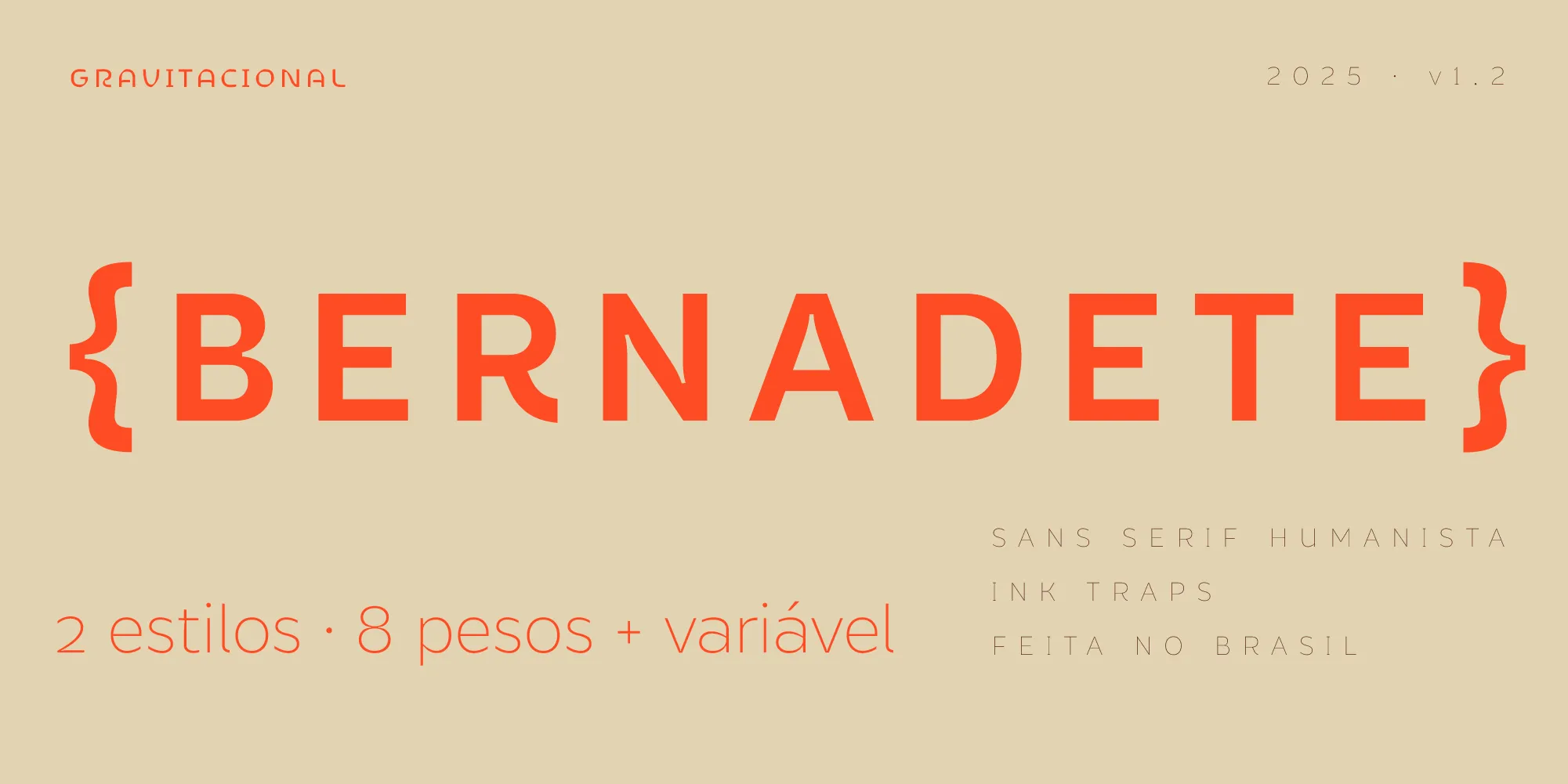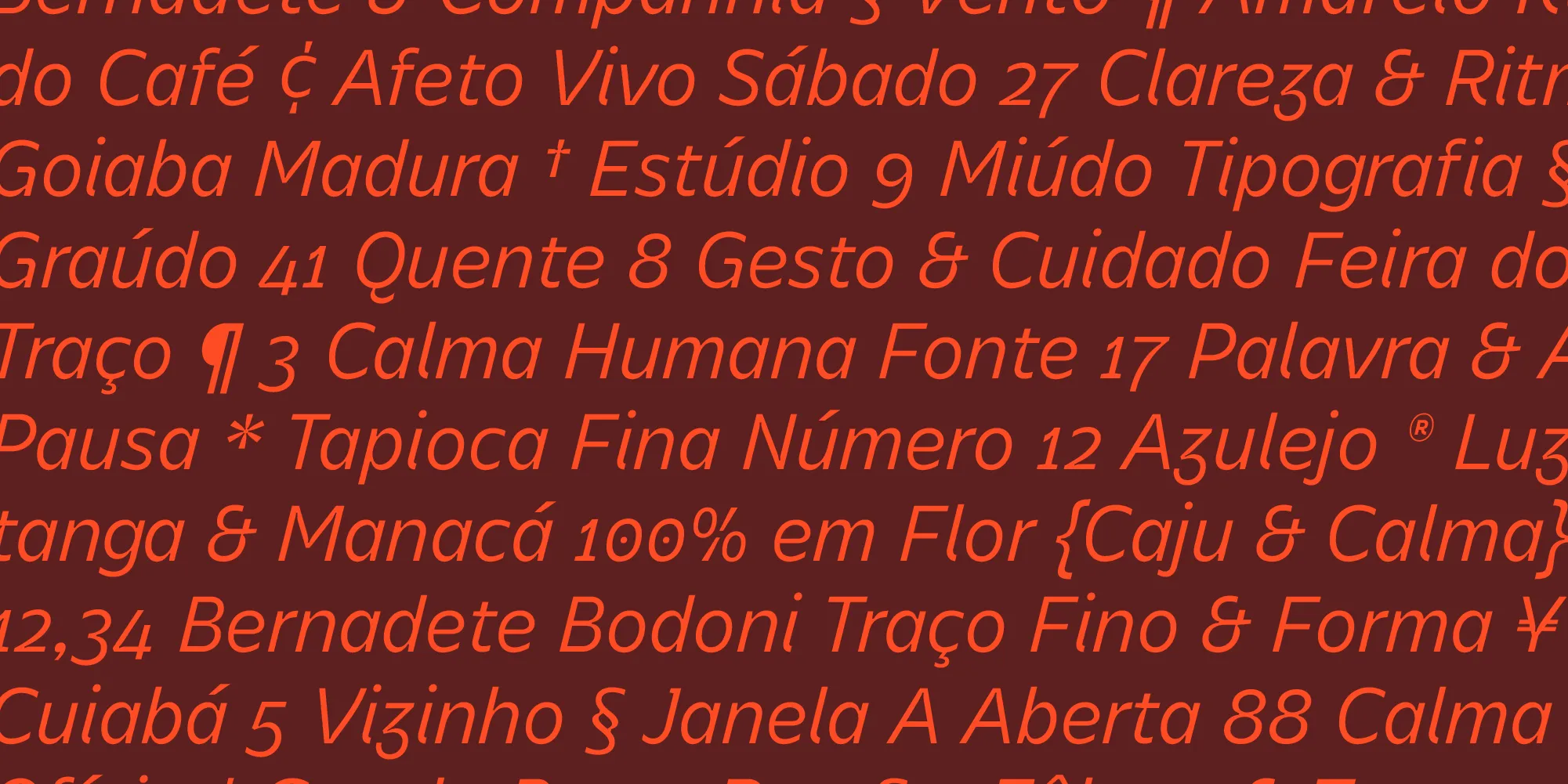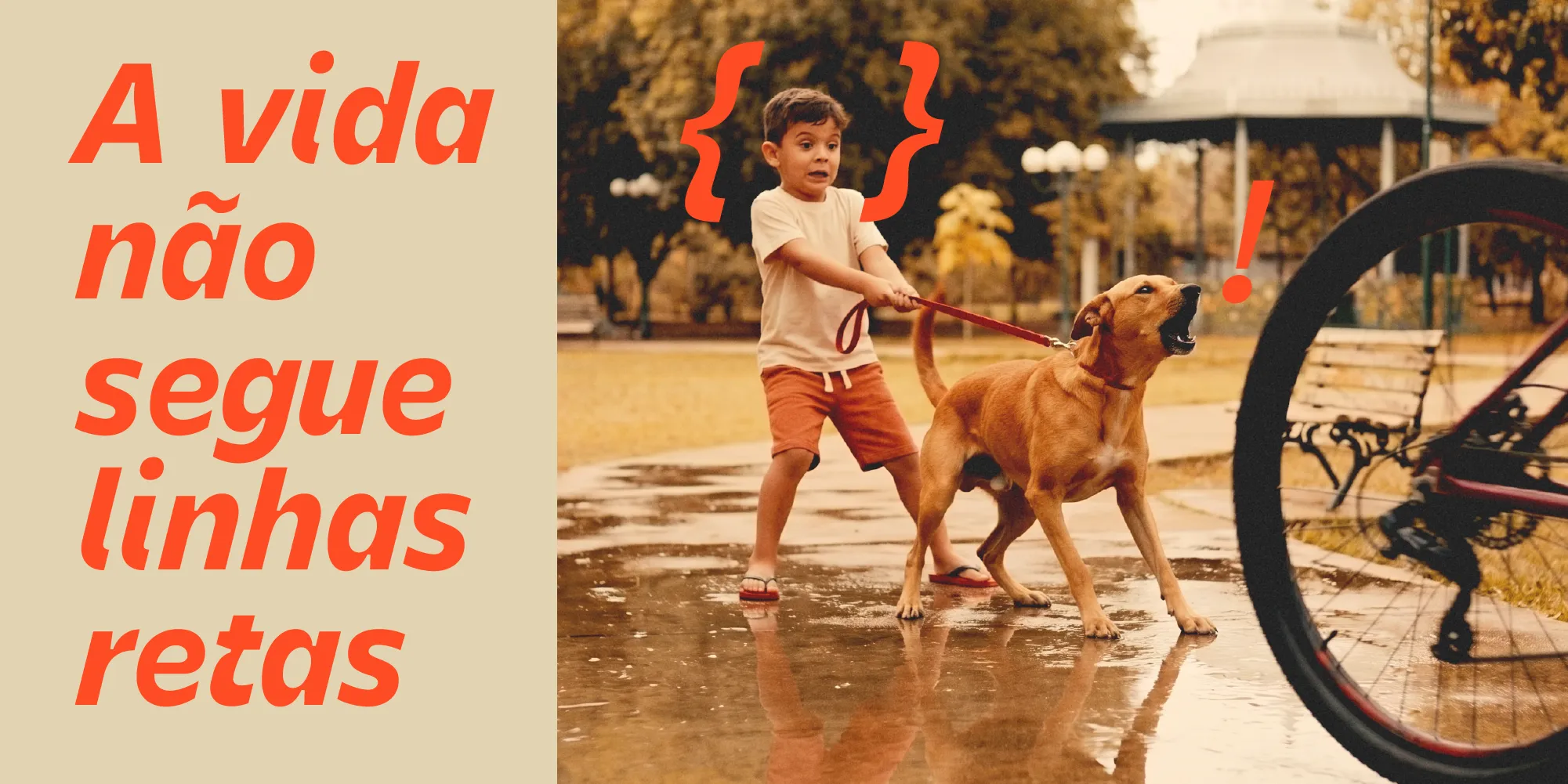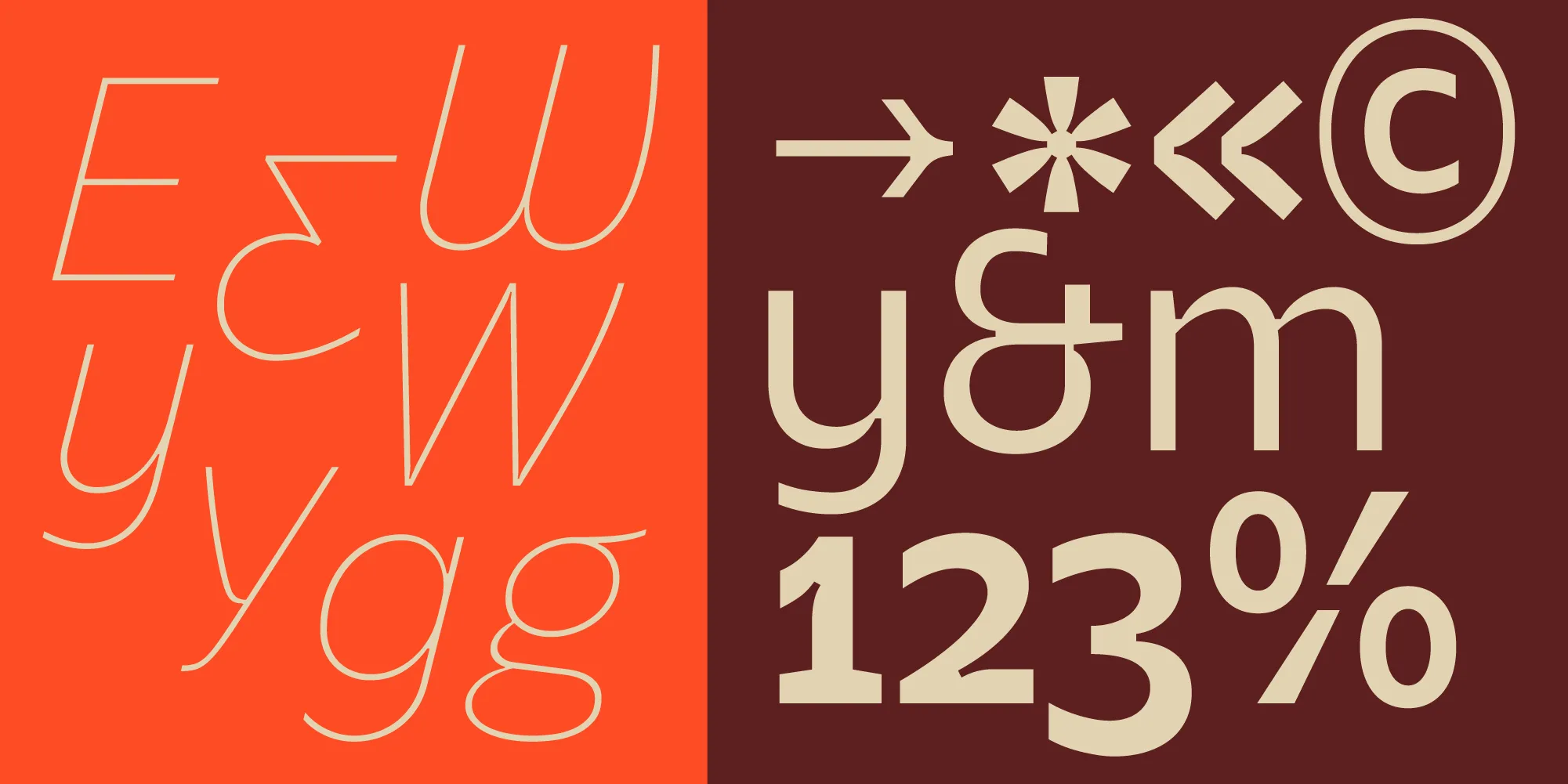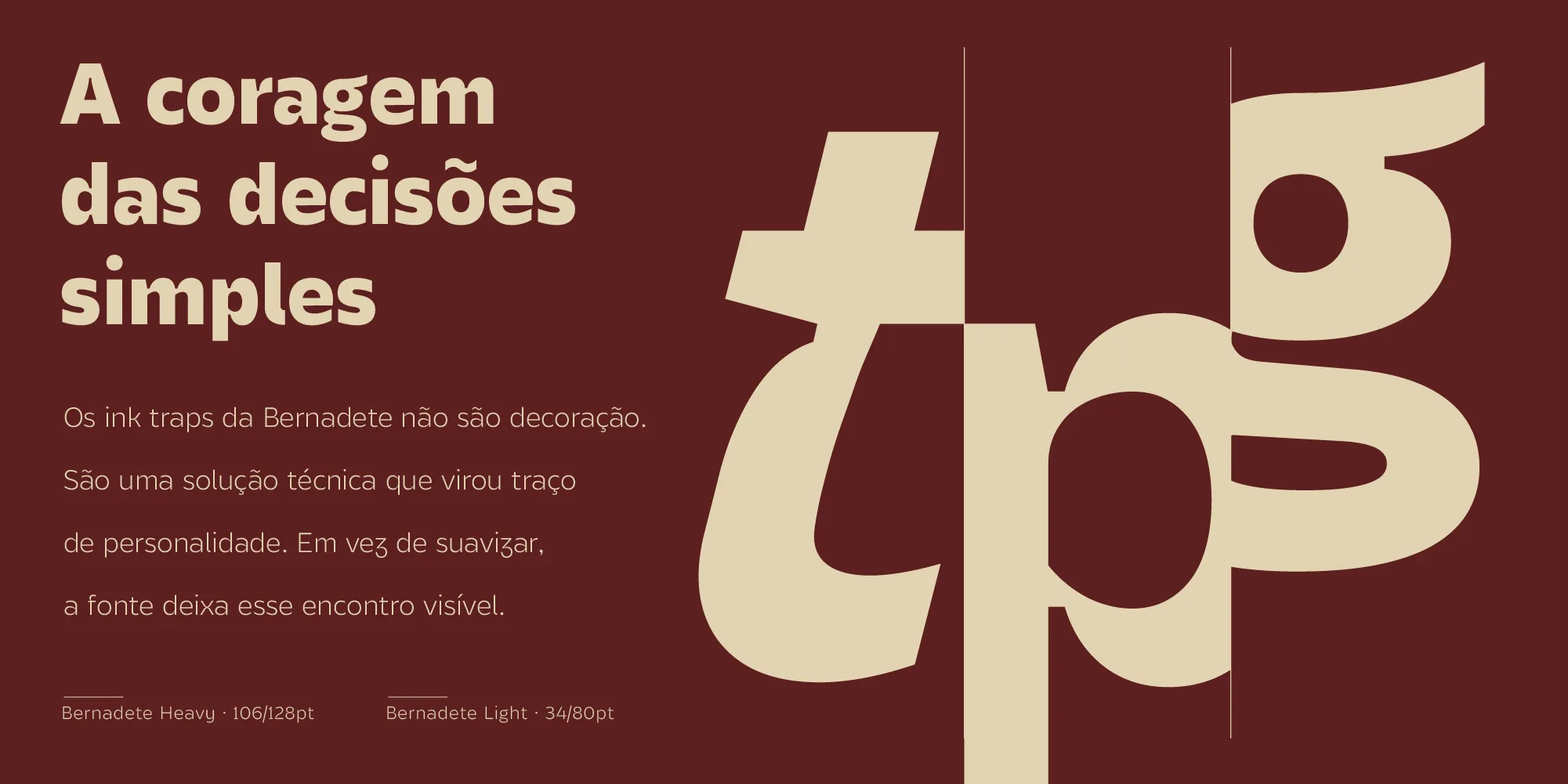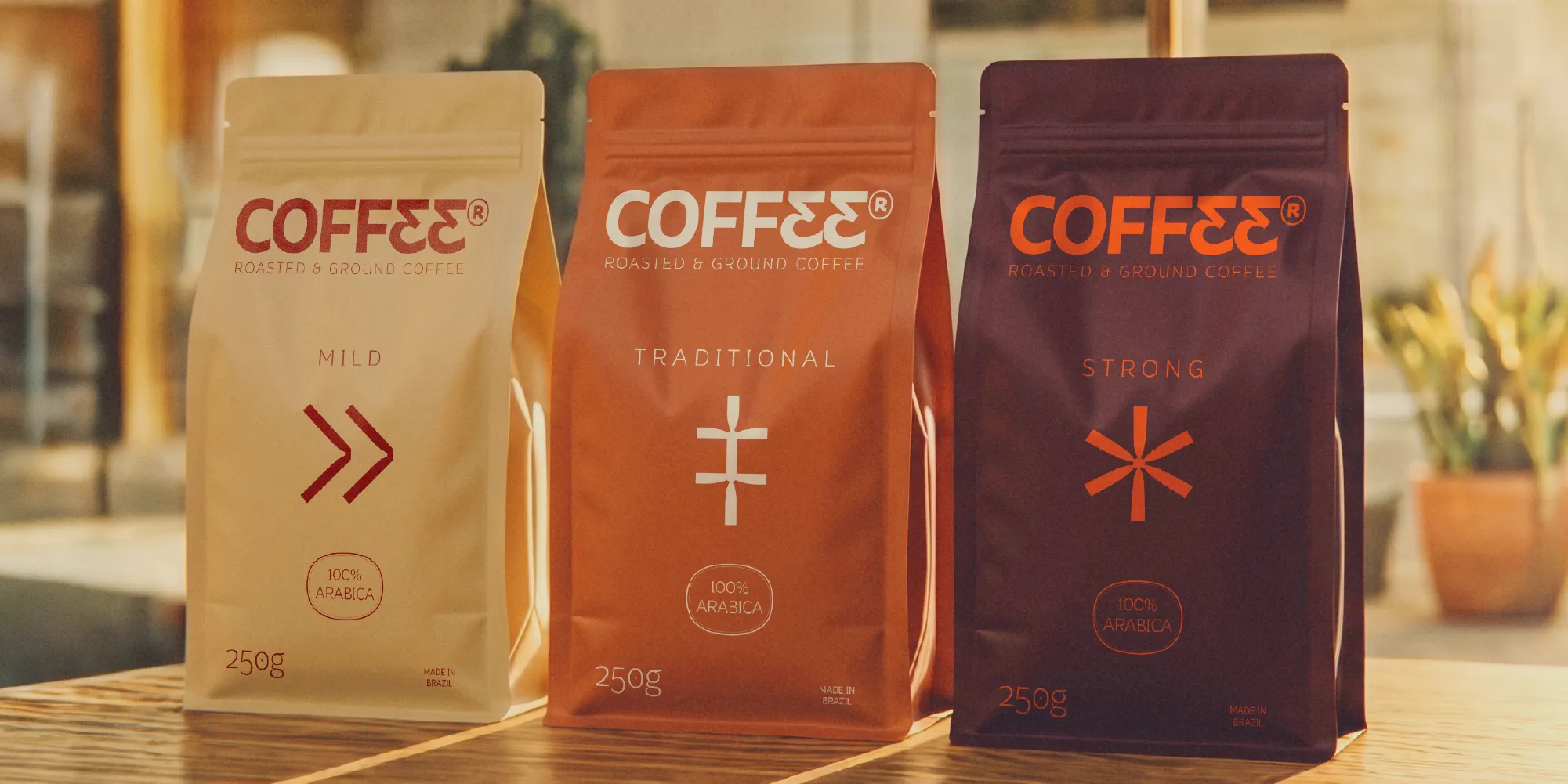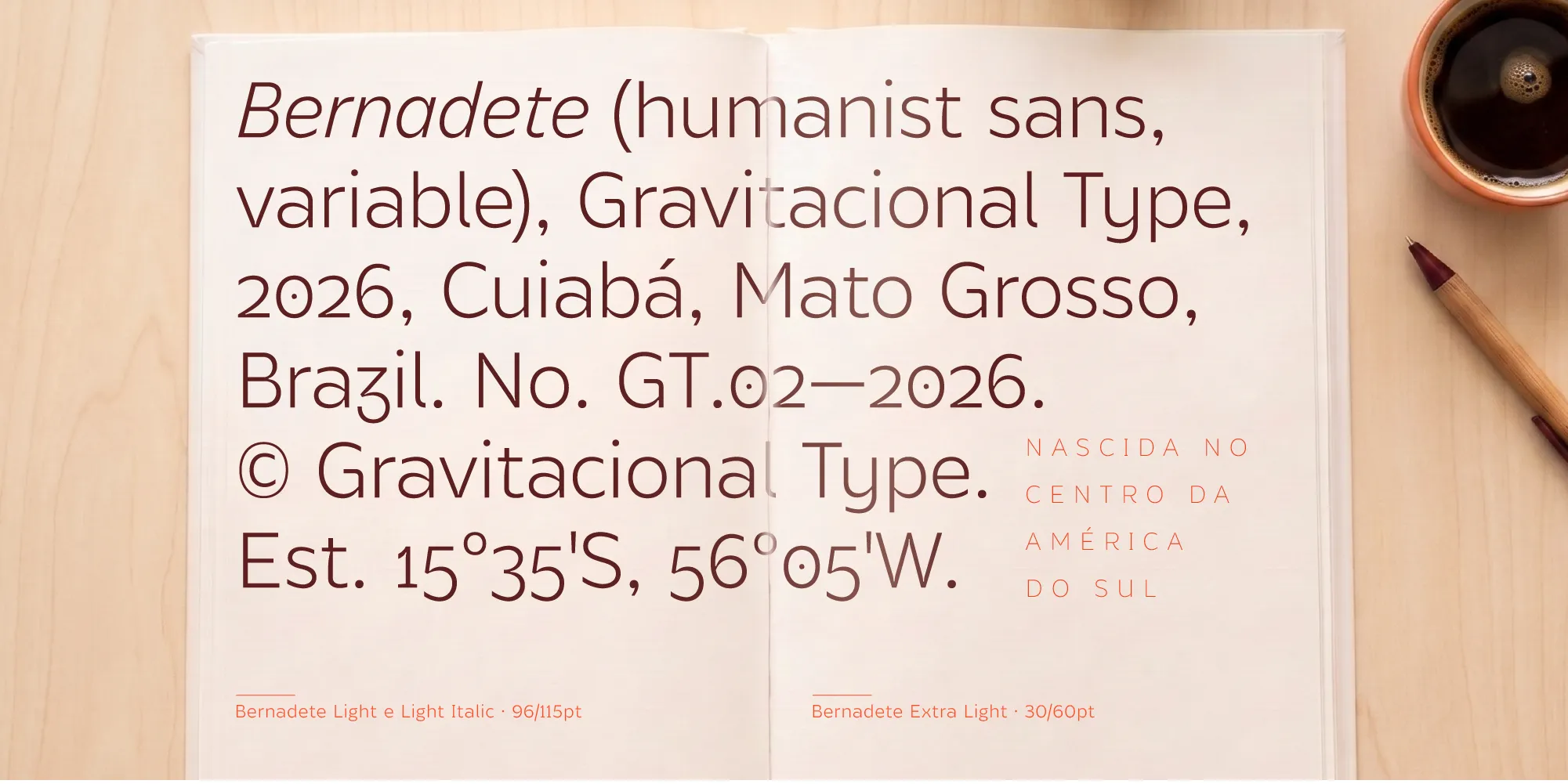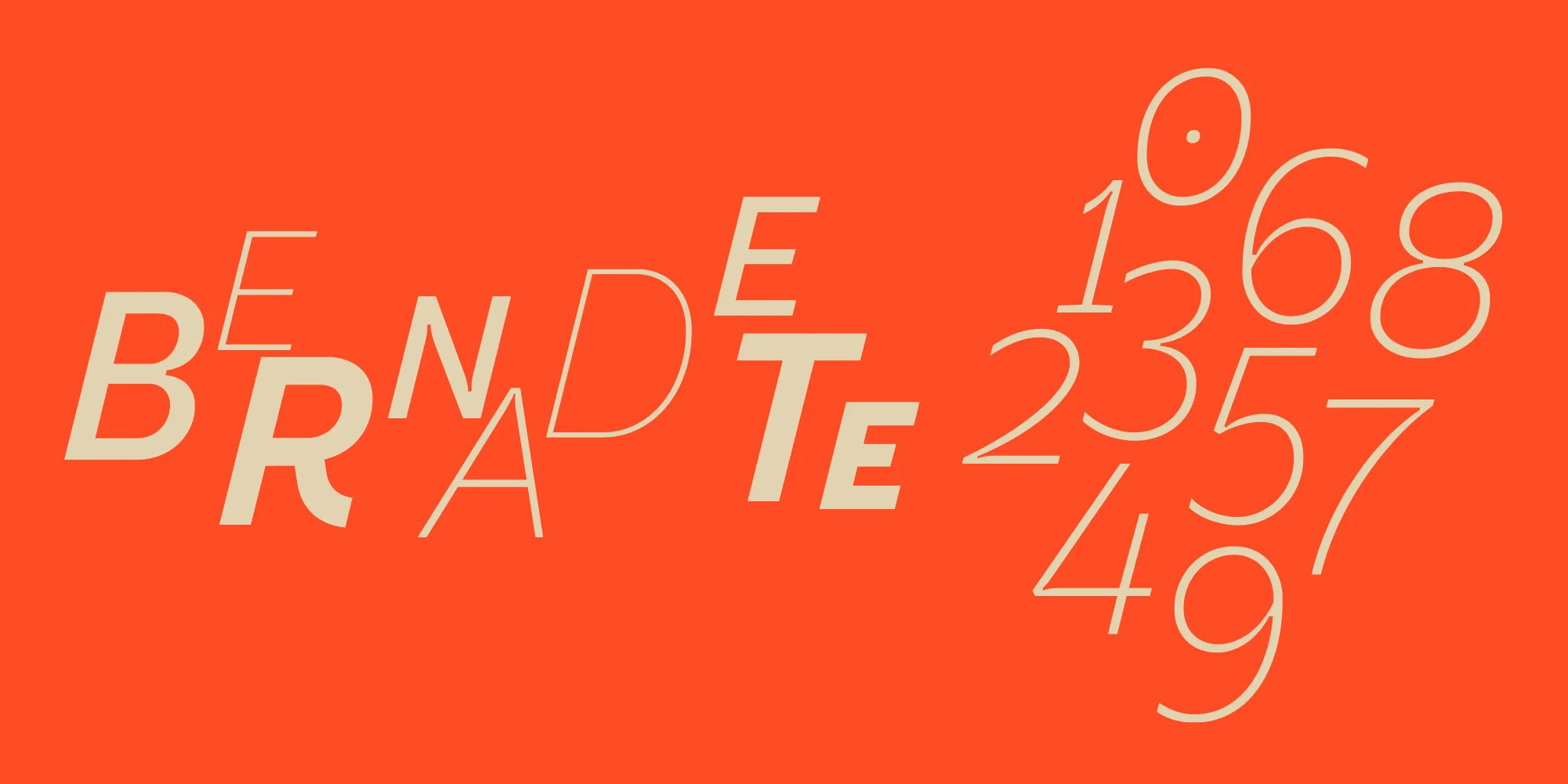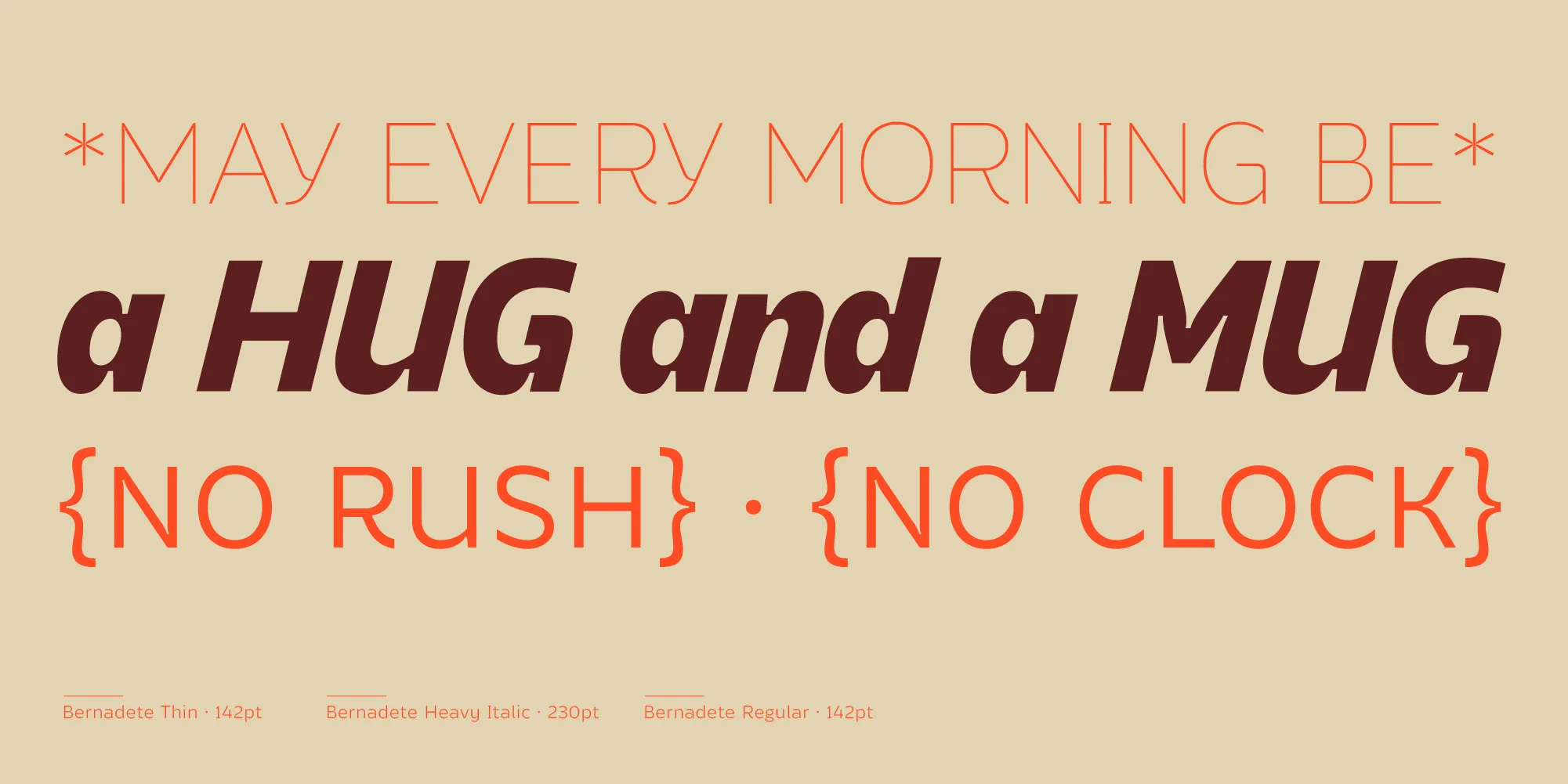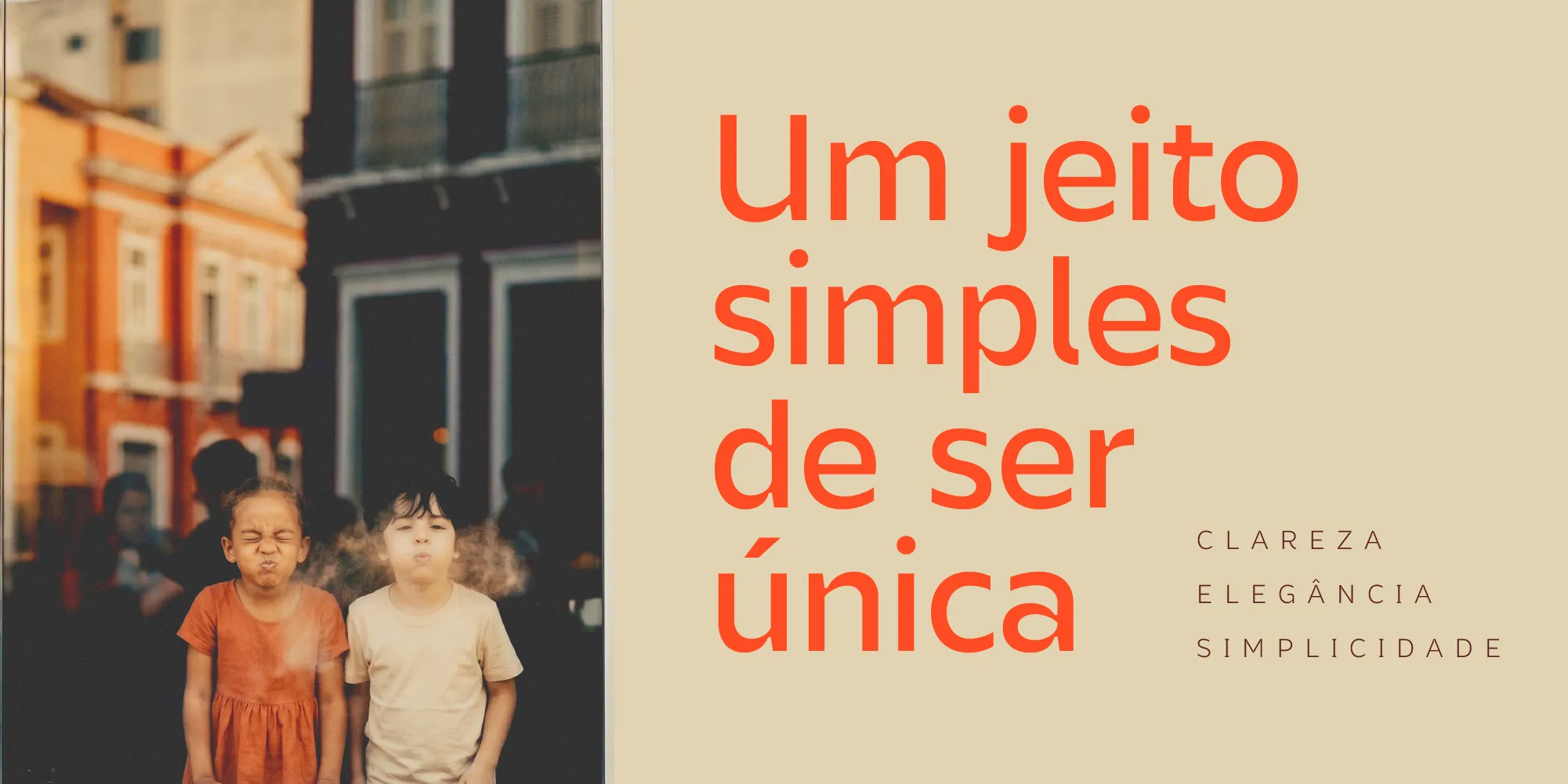
Bernadete é uma família sem serifa humanista. Tem estrutura, mas também tem respiro, calor e ritmo próprio.
É discreta sem ser neutra. Pensada para projetos que precisam de clareza e presença ao mesmo tempo, ela funciona bem no texto corrido sem abrir mão do caráter. Quando você para pra olhar, os gestos aparecem: o z com traço manuscrito, o y com desenho próprio, os ink traps evidentes e assumidos. Não estão ali para esconder. Estão ali porque fazem parte do que ela é.
As formas são limpas, mas há calor no traço. As aberturas generosas e o espaçamento cuidadoso favorecem a leitura em diferentes contextos e tamanhos. O itálico tem feições próprias — mais manuais, mais vivas.
Bernadete nasceu como homenagem e cresceu como projeto. O que começou pensado para títulos acabou se revelando mesmo no texto longo. É nesse lugar — entre o que é preciso e o que é vivo — que ela encontra sua voz.